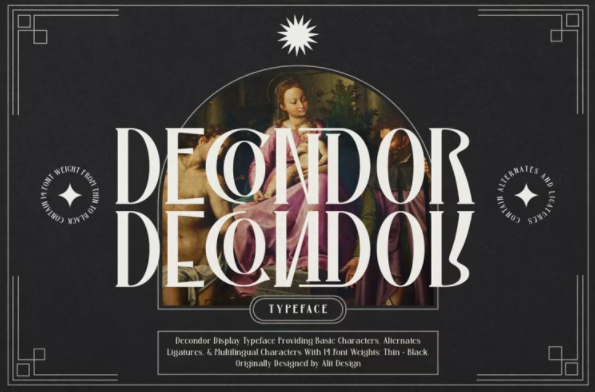
[Fontbundles] Decondor Typeface (2021)
Семейство шрифтов DECONDOR состоит из 14 семейств, от тонких до тяжелых шрифтов. Элегантный современный шрифт создает уникальный дизайн и обязательно привлечет внимание целевой аудитории, занимающейся дизайном. Помимо уникальности, шрифт DECONDOR также обладает роскошным простым характером, что придает дизайну очарование и классическую роскошь.
Эти шрифты идеально подходят для дизайна с концепцией элегантности, роскоши, романтики, моды, классического королевского стиля и так далее.
Особенности:
Набор символов A-Z
семейство (тонкий-тяжелый)
Цифры и штампы; пунктуация (стандарт OpenType)
Стилистические альтернативы
Многоязычный
Лигатуры